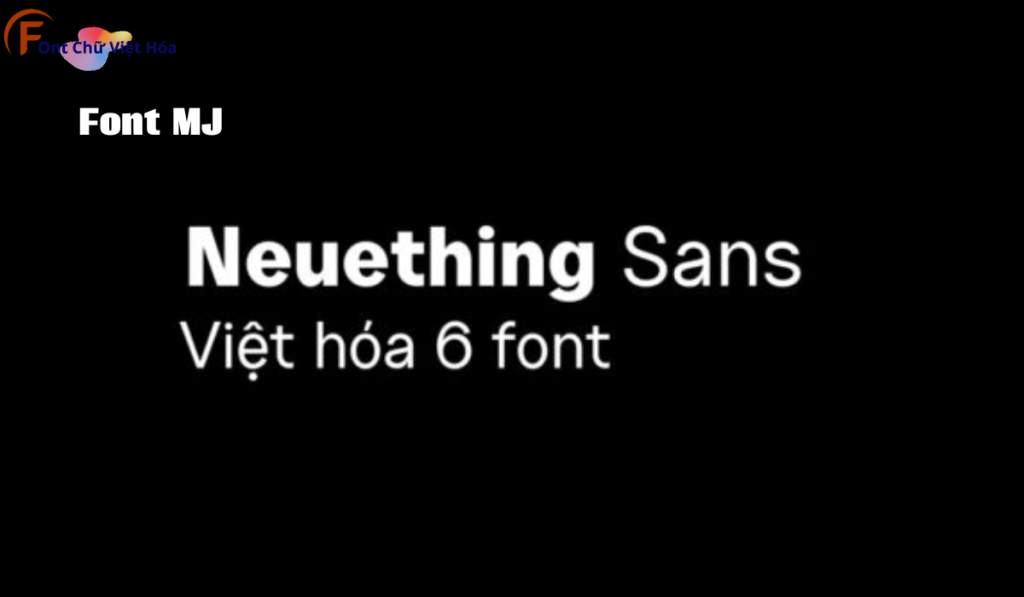
Font MJ Neuething Sans Việt Hóa
Tác giả: MJ Neuething Sans
Bộ Font: MJ
Font MJ Neuething Sans Việt Hóa là một font chữ sans-serif hiện đại, thuộc bộ font MJ. Được thiết kế với mục tiêu mang lại sự thanh lịch và tinh tế, font này lý tưởng cho các dự án thiết kế như website, tài liệu, và bao bì sản phẩm. Với các nét chữ rõ ràng và độ dày đều đặn, Font MJ Neuething Sans Việt Hóa không chỉ dễ đọc mà còn tạo cảm giác chuyên nghiệp. Việc Việt hóa font giúp người dùng dễ dàng sử dụng trong các thiết kế tiếng Việt, mang lại sự tiện lợi và thẩm mỹ cao.